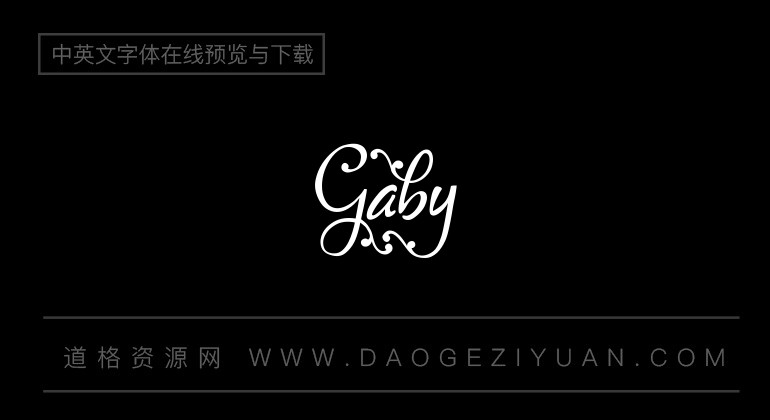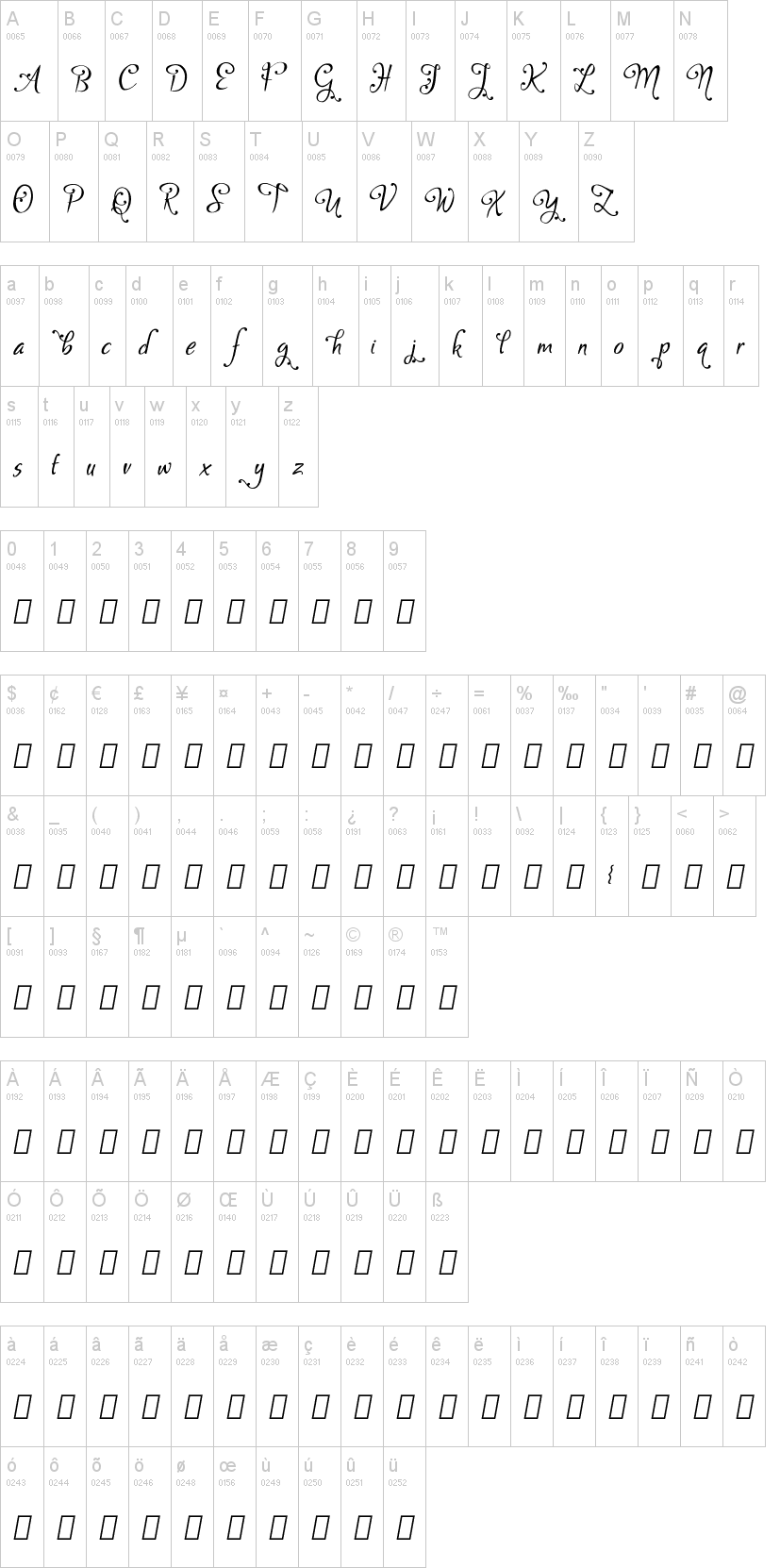
Gaby 字体是一款简洁、现代的英文字体,它由荷兰设计师 Marcelo Melo 设计,是一款多功能的字体,可用于品牌标识、标题、广告等等。Gaby 字体的特点是具有强烈的字符变形,它的设计灵感来源于传统的英文字体,但又不失现代感。Gaby 字体的字符结构具有良好的可读性,可以满足多种设计要求,是一款十分适用的字体。内容介绍
Gaby是一款非常不错的手写艺术字体,具有很好的视觉感,适合于文化类的宣传设计、商业类品牌的广告和产品包装设计以及个性化文字排版等较多场景。